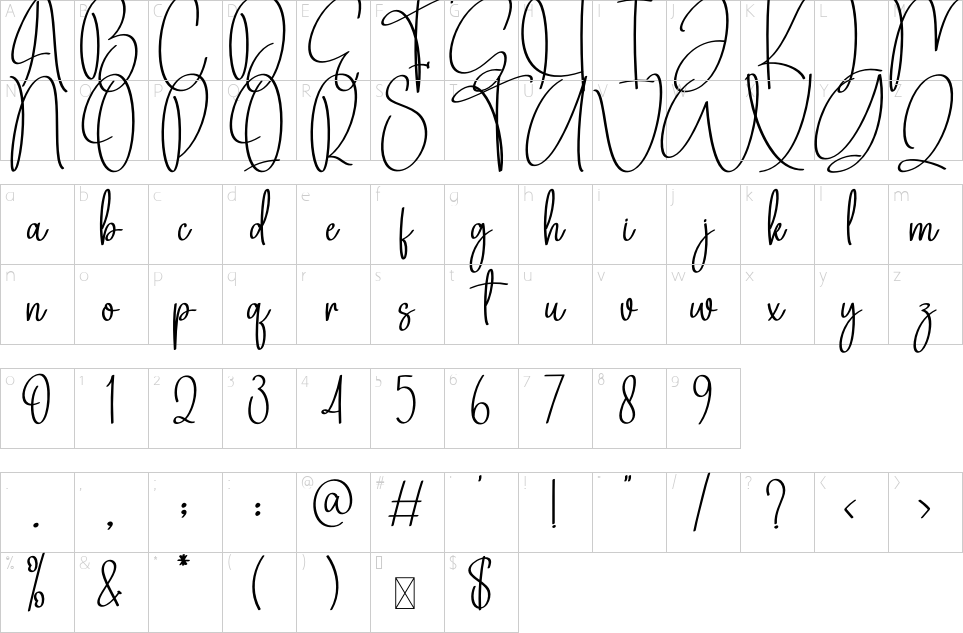
A fonte Gratitude é uma seleção ideal para quem busca expressar a gratidão de maneira agradável e envolvente. Desenvolvida por scratchones, esta fonte já teve 407 downloads no Windows e Mac. Ela oferece um estilo natural que pode ajudar a dar vida a mensagens emocionantes e inspiradoras em suas produções digitais. Com uma linguagem amigável e harmoniosa, a Gratitude é perfeita para criar um ambiente de gratidão em seus projetos, seja em design gráfico, editorial ou até mesmo em escrita digital personalizada. Agradecemos pela escolha desta fonte que encoraja expressões sinceras e positivas através do texto.